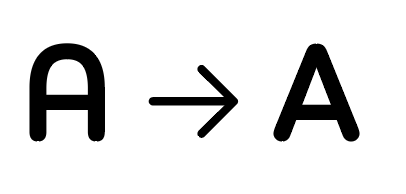
Austausch Schriftzeichen im Zeichensatz
Unsere Firma plant die Bouba Round als zweite Hauschrift einzuführen. Im Zeichensatz ist als Standard ein abgerundetes großes „A“ definiert (s.A.), welches durch ein alternatives eckiges „A“ ersetzt werden kann. Wir würden  gerne aus ästhetischen Gründen das eckige „A“ bevorzugen. Ich hatte Fontshop auch schon kontaktiert, ob sie nicht die Zeichen im Zeichensatz tauschen könnten.
Lässt sich hier wirklich nichts machen?
Wir wollen schon über alle Medien (Online/Print) einheitlich bleiben und eine händische Korrektur jedes mal vermeiden. Gerade bei der Verwendung auf der Website ist mir nicht bekannt, wie sich das alternative Zeichen auslesen und darstellen lässt.
Zuerst einmal sei hier herzlich willkommen! Du könntest @HVD fragen, ob er Euch das modifiziert, denn er hat die Schrift auch entworfen.
Ich habe die Schrift selbst nicht, aber Du kannst die Opentype-Features in Word und in den Layout-/Graphikprogrammen nutzen. Ich vermute mal, dass sich das A im stylistic set 02 verbirgt (03 und 04 haben auch Alternativzeichen). Im Browser geht das wie hier beschrieben: https://css-tricks.com/almanac/properties/f/font-feature-settings/
Wie schon gesagt: direkt beim Schrifthersteller fragen. Je nach dessen Workflow kann sowas recht unproblematisch erstellt werden. Es ist aber wirklich die einzig saubere Methode, es mit den offenen Daten des Schriftherstellers zu machen, statt an der fertigen Schrift herumzudoktern. Technisch möglich ist es freilich. Ein leicht zugängliches Tool ist der Fontsquirrel Generator. Der kann OpenType-Austauschzeichen zu den Standardzeichen machen. Man greift damit aber deutlich in die Schrift ein und es können andere Dinge eventuell nicht mehr wie gewünscht funktionieren. Von den Lizenzbedingungen mal ganz abgesehen.